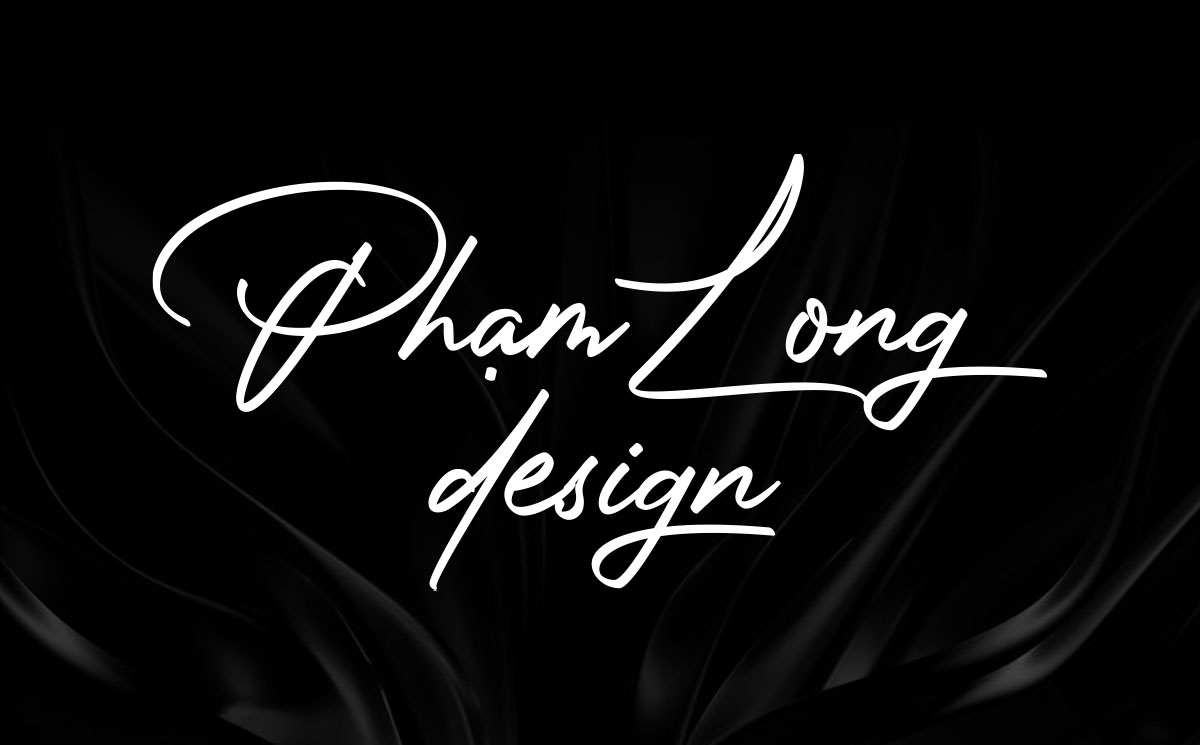
TH Photograph Signature là bộ font chữ viết tay cao cấp được thiết kế riêng cho các ấn phẩm đám cưới, thiết kế thương hiệu và nhiếp ảnh nghệ thuật. Với các đường nét uyển chuyển, thanh lịch và đã được Việt hóa trọn bộ, font chữ này mang đến diện mạo sang trọng và dấu ấn cá nhân đậm nét cho mọi dự án. Đây chính là sự lựa chọn hoàn hảo để nâng tầm tính thẩm mỹ cho thiệp cưới, album ảnh và các thiết kế lãng mạn của bạn.
Font Chữ Viết Tay Cho Đám Cưới TH Photograph Signature – Đỉnh Cao Nghệ Thuật Nét Chữ Sang Trọng Cho Ngày Trọng Đại
Trong không gian tiệc cưới hiện đại, từng chi tiết nhỏ đều góp phần tạo nên dấu ấn khó quên cho ngày trọng đại. Việc lựa chọn một kiểu chữ đại diện cho câu chuyện tình yêu của cô dâu và chú rể đòi hỏi sự tinh tế, chỉn chu và khác biệt. Font chữ viết tay cho đám cưới TH Photograph Signature ra đời nhằm đáp ứng hoàn hảo nhu cầu đó, mang lại cảm giác chân thật, ấm áp nhưng không kém phần đẳng cấp.
Được truyền cảm hứng từ những nét chữ ký mềm mại của các nghệ nhân calligrapher chuyên nghiệp, TH Photograph Signature tái hiện trọn vẹn sự tự nhiên và phóng khoáng trong từng đường nét. Mỗi ký tự đều được chăm chút kỹ lưỡng về độ nghiêng, khoảng cách kerning và độ đậm nhạt của nét bút, giúp các bản thiết kế thiệp cưới hay logo nhiếp ảnh trở nên sống động và có hồn hơn bao giờ hết.
1. Nét Vẽ Uyển Chuyển, Tự Nhiên Như Chữ Ký Tay Thật (Handwritten Authenticity)
Điểm nổi bật nhất của TH Photograph Signature chính là khả năng mô phỏng nét viết tay tự nhiên một cách chân thực nhất. Không bị gò bó bởi các quy chuẩn phông chữ máy tính cứng nhắc, bộ font này sở hữu những đường cong uốn lượn nhịp nhàng, mô phỏng lại nét bút mực di chuyển trên chất liệu giấy mỹ thuật cao cấp. Sự tự nhiên này tạo nên cảm giác gần gũi, tinh tế, vô cùng phù hợp cho các cặp đôi muốn gửi gắm tình cảm chân thành đến từng vị khách mời thông qua chiếc thiệp cưới trân quý.
2. Hỗ Trợ Tiếng Việt Đầy Đủ Và Tích Hợp Ký Tự Thay Thế Đa Dạng (Vietnamese & Swashes)
Một trong những rào cản lớn nhất khi sử dụng các font chữ viết tay nước ngoài là việc thiếu dấu Tiếng Việt hoặc dấu bị lệch chuẩn gây mất thẩm mỹ. Với TH Photograph Signature, vấn đề này đã được giải quyết hoàn toàn. Font chữ đã được Việt hóa chỉn chu, các dấu thanh (hỏi, ngã, sắc, huyền, nặng) được tinh chỉnh tỉ mỉ để hòa hợp với độ nghiêng của chữ. Bên cạnh đó, font còn tích hợp hệ thống ký tự thay thế (Alternate Glyphs) và nét uốn trang trí (Swashes) ở đầu và cuối từ, giúp người thiết kế dễ dàng biến tấu tên cô dâu chú rể thành những tác phẩm nghệ thuật độc bản.
3. Ứng Dụng Đa Năng Từ Thiệp Cưới, Album Ảnh Đến Bộ Nhận Diện Thương Hiệu
Mặc dù được tối ưu hóa làm font chữ viết tay cho đám cưới, TH Photograph Signature vẫn thể hiện tính đa năng vượt trội trong nhiều lĩnh vực sáng tạo khác:
- Thiết kế thiệp cưới & Ấn phẩm cưới: Sử dụng cho phần tên cô dâu chú rể, tiêu đề thiệp cưới, bảng Welcome, menu tiệc cưới, thẻ cảm ơn (Thank you card).
- Watermark nhiếp ảnh: Làm dấu ấn chữ ký cá nhân bảo vệ bản quyền cho các nhiếp ảnh gia cưới (Wedding Photographer) trên các bộ ảnh Studio hay Ngoại cảnh.
- Nhận diện thương hiệu (Branding): Tối ưu cho logo các thương hiệu váy cưới, Studio chụp ảnh, dịch vụ Wedding Planner, cửa hàng hoa tươi và mỹ phẩm cao cấp.
- Truyền thông mạng xã hội: Sáng tạo các hình ảnh Banner, Quote tình yêu, Story Instagram tràn đầy cảm xúc.
5. Phong Cách Nghệ Thuật Hiện Đại Kết Hợp Cổ Điển (Modern Classic Vibe)
TH Photograph Signature khéo léo kết hợp giữa vẻ đẹp thanh lịch của thư pháp cổ điển và hơi thở phóng khoáng của thiết kế hiện đại. Nét chữ không quá cầu kỳ rườm rà nhưng vẫn giữ được sự bay bổng cần thiết, giúp tổng thể bản thiết kế luôn giữ được độ thoáng, dễ đọc và sang trọng. Đây là yếu tố then chốt giúp các sản phẩm thiết kế không bị demode (lỗi mốt) theo thời gian.
Bí Quyết Sử Dụng Font TH Photograph Signature Trong Thiết Kế Đạt Hiệu Quả Thẩm Mỹ Cao Nhất
Để font chữ viết tay cho đám cưới TH Photograph Signature phát huy tối đa vẻ đẹp trong không gian thiết kế, bạn có thể áp dụng một số kinh nghiệm phối chữ chuyên nghiệp sau:
- Kết hợp với font chữ không chân (Sans-serif) hoặc có chân (Serif) tối giản: Hãy dùng TH Photograph Signature cho các phần điểm nhấn như Tên cô dâu chú rể, Từ khóa chính. Các thông tin chi tiết như ngày tháng, địa điểm nên dùng font chữ đứng đơn giản để đảm bảo tính dễ đọc.